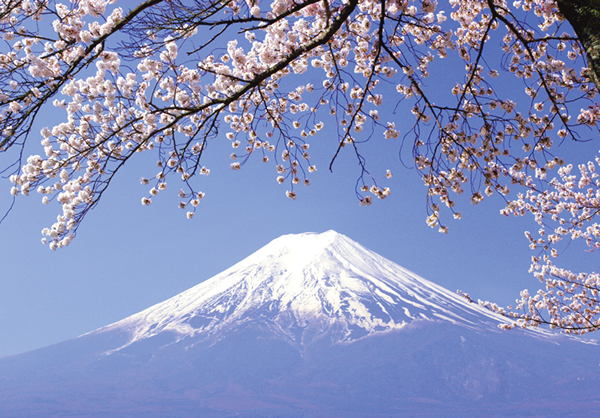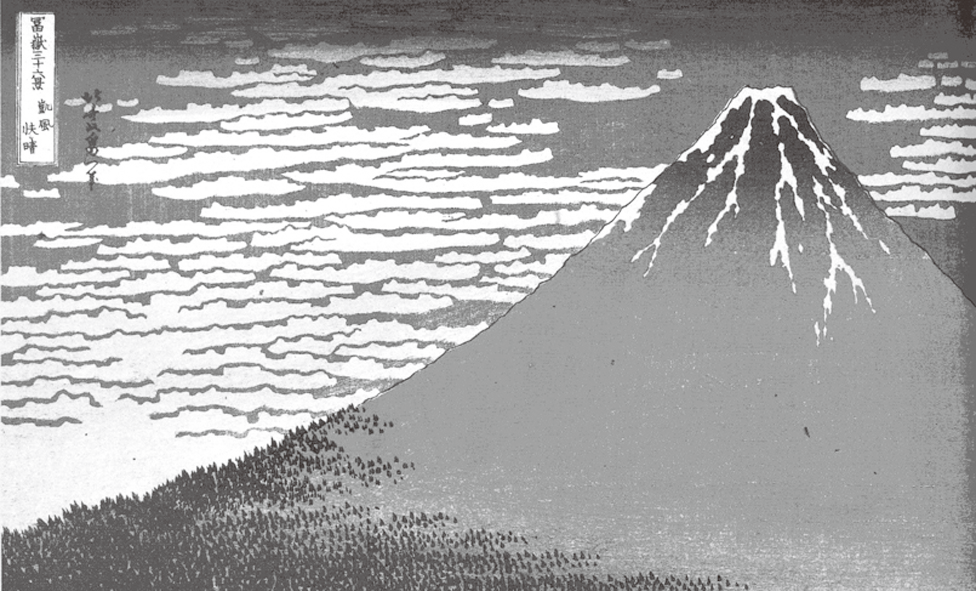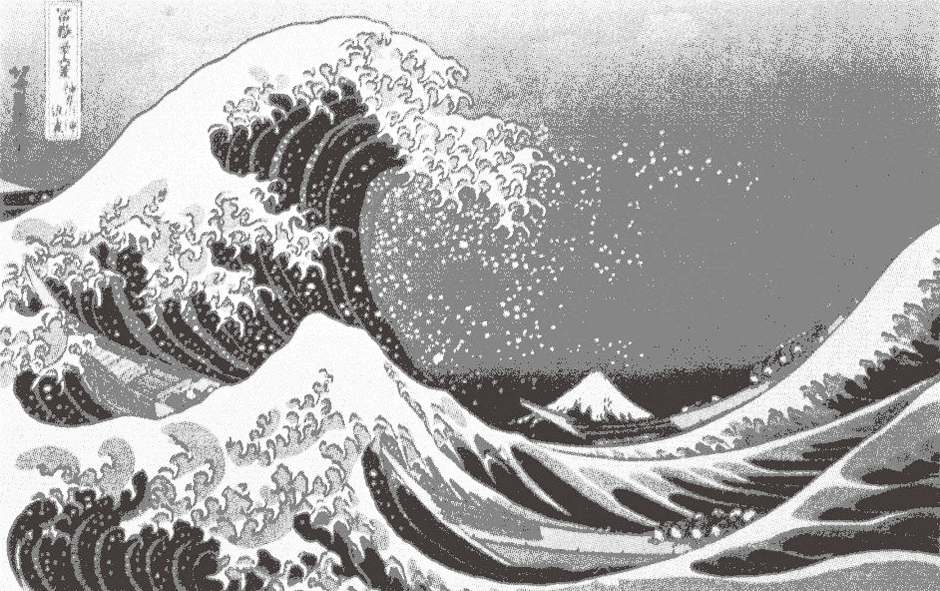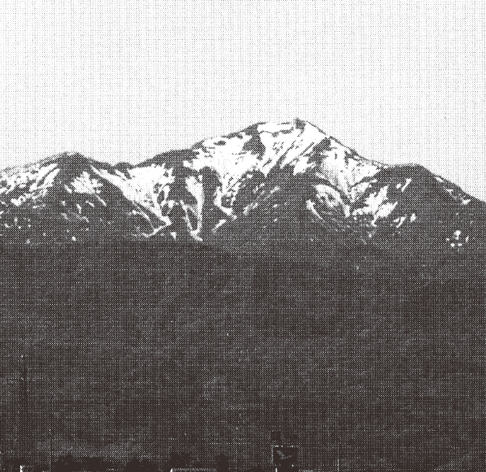
「ふじは日本一の山」と巌谷小波が童謡に歌ったのは明治43年(1910)であった。富士山の雄大、清純な姿は、昔から文学や絵画などに登場している。万葉集の山部赤人は「田兒の浦ゆうち出でて見れば真白にぞ不尽の高嶺に雪は降りける」と詠んでいる。浮世絵では、葛飾北斎の富嶽三十六景の「赤富士」や「神奈川沖浪裏」は富士山の美しさを追求した傑作。近代作家で富士山を画題にした画家は、横山大観の他に多くいる。
全国には、富士山に形が似ているため「○○富士」と呼ばれる山がある。北から見てみると、利尻富士(利尻山)、斜里富士(斜里岳)、阿寒富士、美瑛富士、蝦夷富士(羊蹄山)、津軽富士(岩木山)、南部富士(岩手山)、出羽富士(鳥海山)、会津富士(磐梯山)、日光富士(男体山)、榛名富士、越後富士(妙高山)、加賀富士(大門山)、大野富士(荒島岳)、諏訪富士(蓼科山)、三河富士(明神山)、伊賀富士(倶留尊山)、近江富士(三上山)、都富士(比叡山)、大和富士(額井岳)、伯耆富士(大山)、石見富士(三瓶山)、八幡富士(飯山)、阿波富士(高越山)、讃岐富士(飯野山)、土佐富士(鴻ノ森)、豊後富士(由布岳)、薩摩富士(開聞岳)など50以上ある。
私のふるさとは新潟県柏崎市。幼い時から米山(よねやま)を見て、日本海で泳ぎ、成長した。暗くてボールが見えなくなるまで遊び、「海は荒海、向うは佐渡よ」(北原白秋・中山晋平)を歌って帰路についた。米山は993でメートル、それほど高くはないが、火山であり、日本海から突き出したさまは、雄大で高山に見える。米山は常に私たちを見守ってくれ、春になると雪解けの形で田植えの時を知らせてくれた。子供の頃には11回、米山登山をした。1981年、米山をイメージして新明朝〈山〉をデザインした。
ふるさとの山は、その地方で誰にでも知られているので、清酒の銘柄に採用されることが多い。北から山の名をつけた清酒を上げると「男山」北海道と富山、「大山」山形、「関山」岩手、「勝山」宮城、「鳳山」仙台、「春日山」新潟など、米所が多い。
歴代横綱でしこ名に山がつく力士とその出身地を示す。「丸山」「秀ノ山」宮城、「太刀山」富山、「栃木山」栃木、「宮城山」岩手、「双葉山」大分、「羽黒山」新潟と続く。
山は高く、遠くから見える大きさがある。山は水をたくわえ、植物や動物や人間を養う。山は風の方向を変え、雨や雪を降らす。ある時には、火を噴いて岩山を造り、湖水も造る。山は登山やハイキングなど、生活に潤いを与えてくれる。
「山」のつく名字は少なくない。上に「山」の字がつくものは約600、下に「山」がつくものは約2100あるという。「山」のつく名字は山本、山田、山口、山崎などがあり、山本は約100万件あるという。山本がなぜこんなに増えたのか。その理由に、人間の居住地で最も良いのは、後ろに山を背負い前に川などのある地形という考えがあるからだ。山本は山のふもとを表わし、山と川の幸を獲り、田畑も作る。敵が攻めてくれば山に逃げ、助けを得る。
聖書の中には、神の家の山が出てくる。『末の日に,エホバの家の山はもろもろの山の頂より上に堅く据えられ…すべての国の民は必ず流れのようにそこに向かう。そして多くの民は必ず行って,こう言う。「来なさい。エホバの山に,ヤコブの神の家に上ろう。神はご自分の道についてわたしたちに教え諭してくださる。わたしたちはその道筋を歩もう」』。イザヤ2:2,3。
山の意味とイメージには他に巨大、安定性、強固、高天、高貴、最高峰、登山、温泉、滝、清里、果実、展望台などがある。